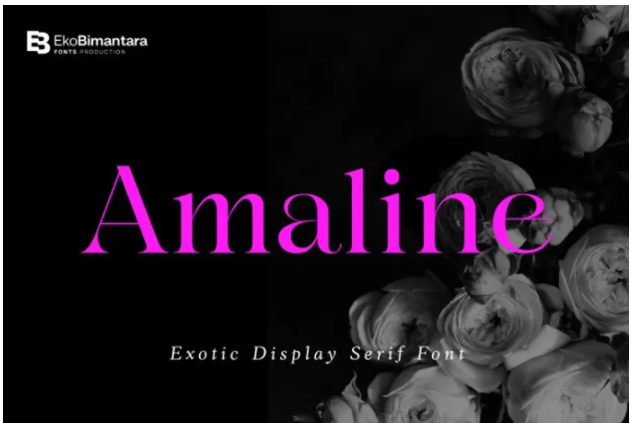
[Fontbundles] Amaline Font (2021)
Fontbundles Amaline Font (2021)
Amaline
- это высококонтрастный, экзотический шрифт с засечками.
Уникальная форма букв демонстрирует элегантность и красоту. Подходит для различных дизайнерских целей.